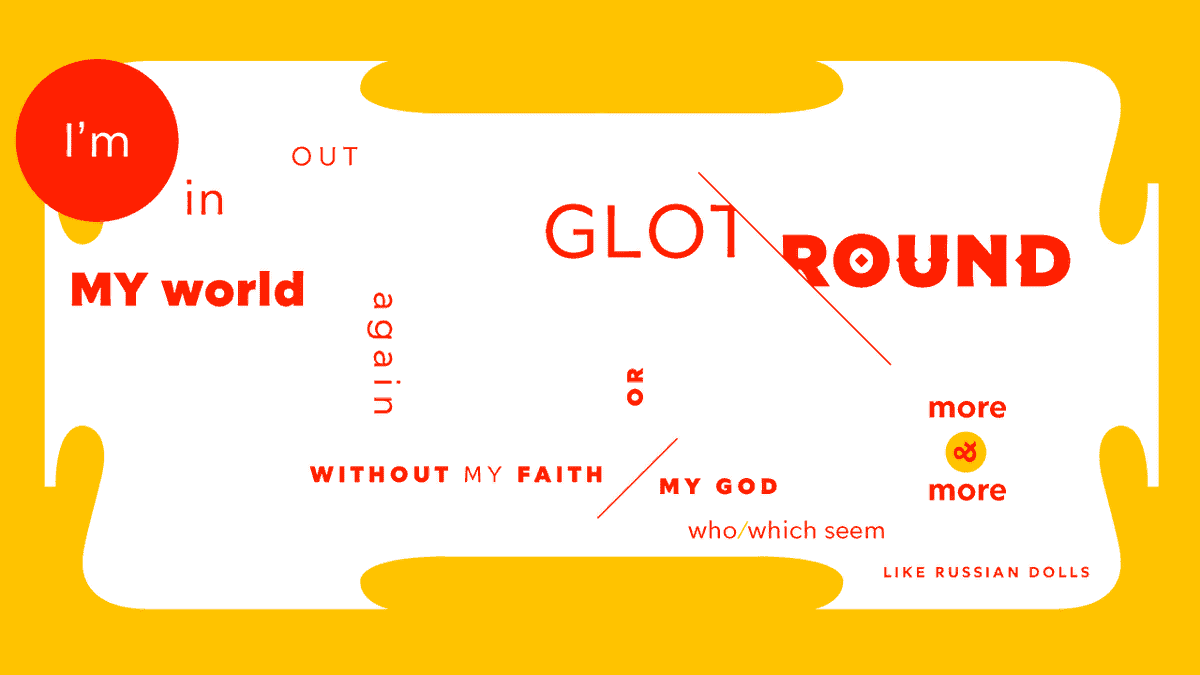
Название: Glot Round Font (2021)
Glot Round - это семейство шрифтов без засечек, состоящее из десяти членов, основанных на сочетании пропорций римских квадратных прописных букв и гиперчитаемых засечек со слегка закругленными углами.
Glot Round представлен в пяти весовых вариантах с соответствующим истинным курсивом: Light, Regular, Medium, Bold и Black. Семейство Glot имеет широкий диапазон и невероятно функционально, оно хорошо подходит как для длинных текстов, так и для дисплейной типографики.
Разработав шрифты для нескольких самых популярных многопользовательских онлайн-игр, мы решили, что настало время перенести поле боя в народ.
Glot Round оснащен широкой языковой поддержкой (Центральная, Восточная и Западная Европа) и альтернативными декоративными шипами OpenType для тех случаев, когда требуется намек на опасность.